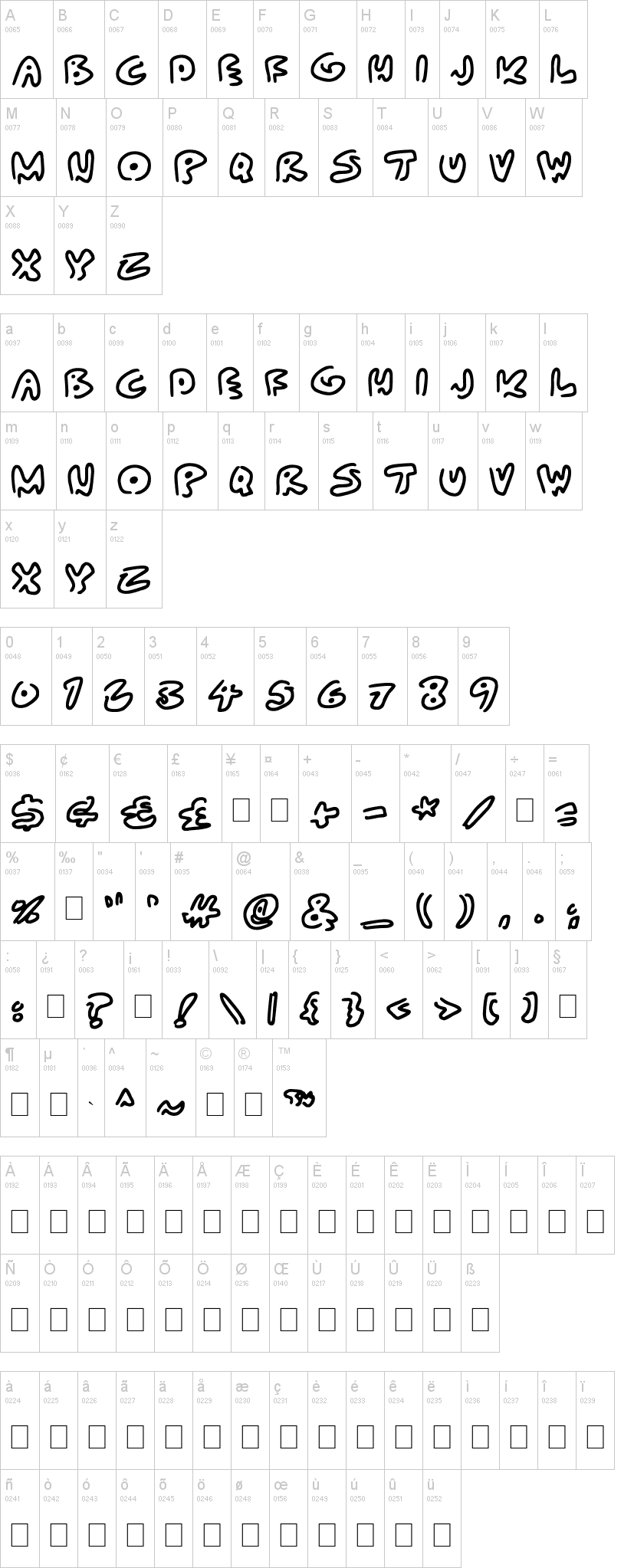
Almost Outlines
Almost Outlines 是一款由 Almost Design Studio 开发的轻量级轮廓字体。它具有简洁、灵活、优雅的设计,可以在任何场景中使用,并且可以自由组合,以满足个性化的需求。它的特点是有趣的轮廓,细节丰富,可以在印刷品、网站、应用程序和其他场景中使用。
Almost Outlines是一款非常不错的手写艺术字体,具有很好的视觉感,适合于文化类的宣传设计、商业类品牌的广告和产品包装设计以及个性化文字排版等较多场景。